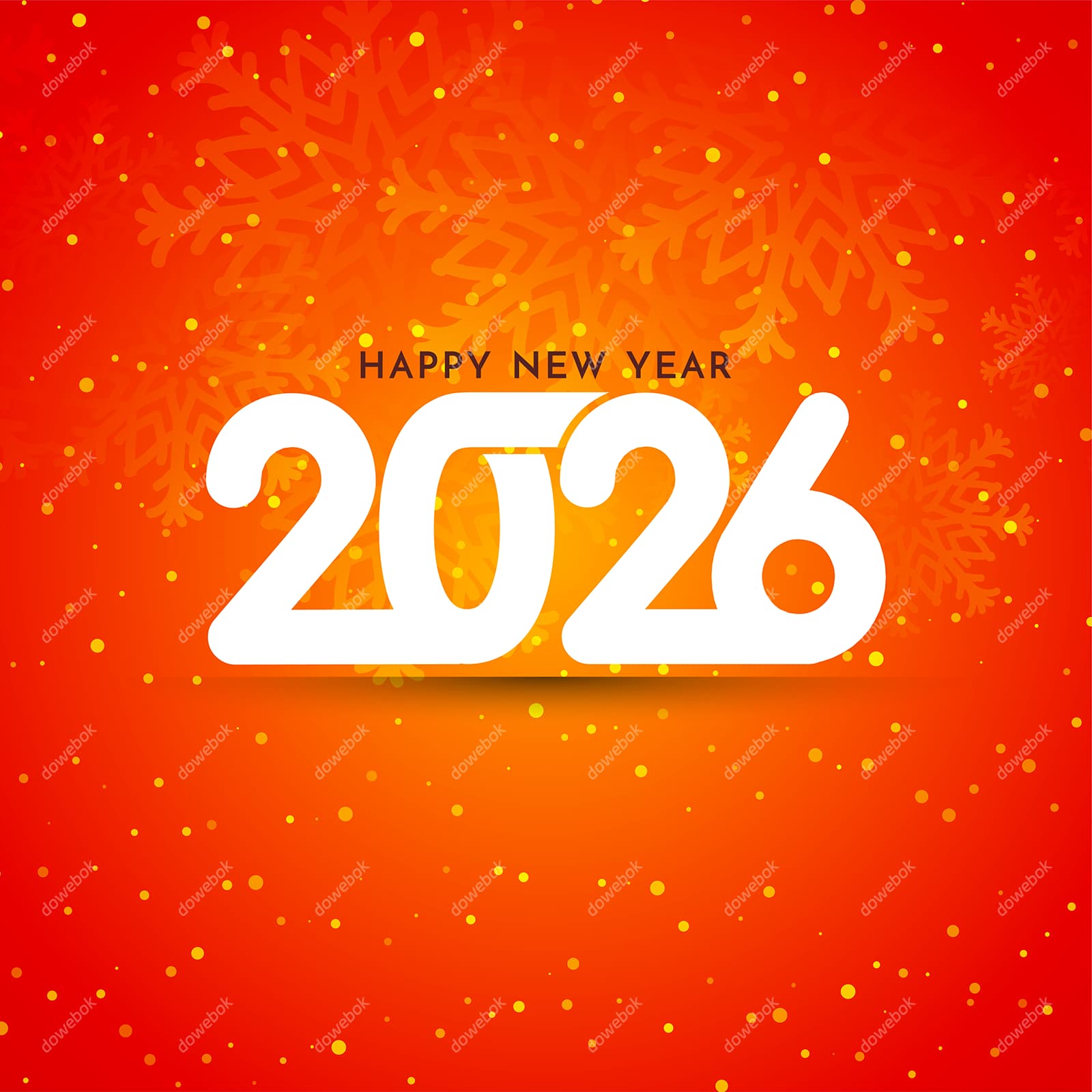
这是一款白色 2026 数字设计的新年快乐矢量素材,橙红渐变背景上,点缀着浅橙色雪花暗纹与细碎金点,营造出热烈又灵动的氛围。画面中央是醒目的白色 “2026” 字体,上方配黑色 “Happy New Year” 英文。整体色调暖艳明亮,既以红橙传递新年的喜庆感,又借雪花元素呼应冬日氛围,视觉活泼且富有节日气息。